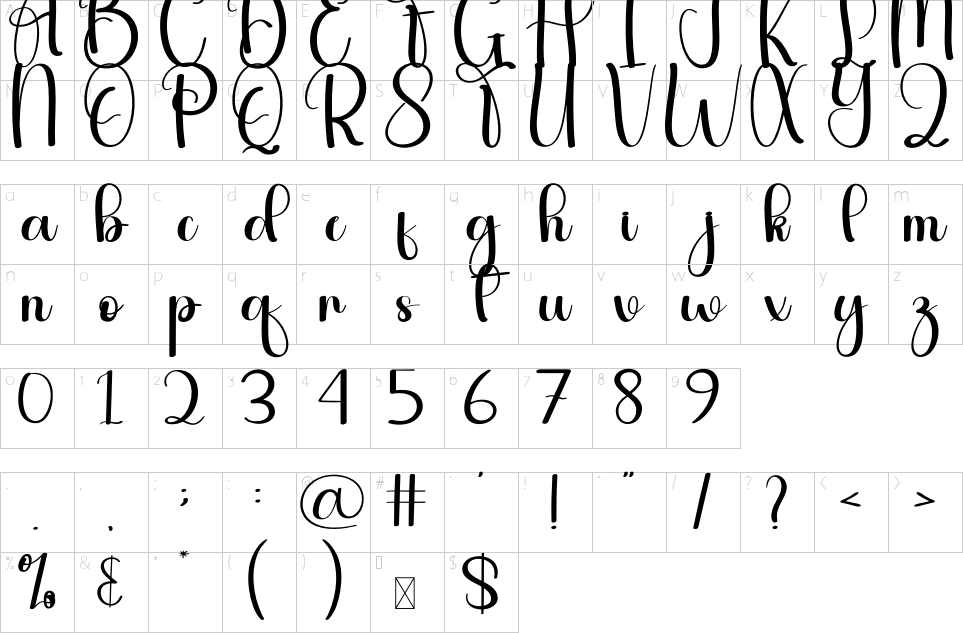
Descubra Autography, uma fonte que traz uma sensação natural e envolvente para seu projeto. Especificamente projetada para quem busca uma fonte que se mistura perfeitamente com textos legíveis, Autography foi cuidadosamente pensada e desenvolvida por William Jhordy. Este fonte foi descarregado 566 vezes, mostrando seu valor e versatilidade. Seja você um designer gráfico, um criador de conteúdo ou até mesmo um blogueiro, Autography pode ser o complemento perfeito para suas necessidades de fontes. Explore a variedade de estilos e usabilidade de Autography e descubra por que mais de 560 pessoas já usam esta fonte de maneira positiva. Tente agora e faça seu projeto se destacar.